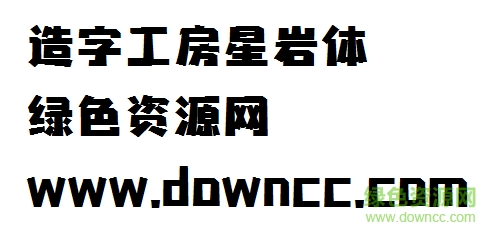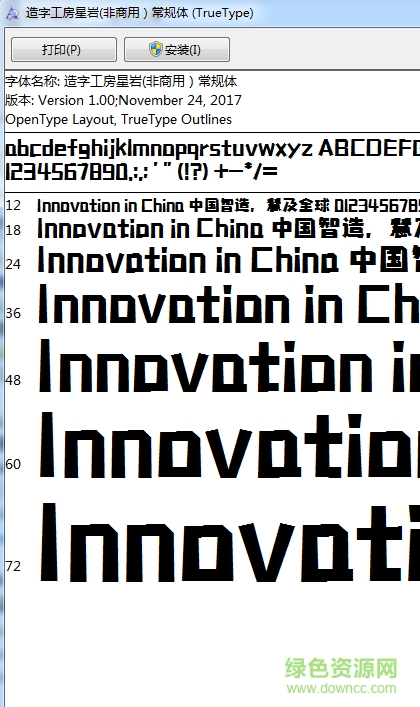
造字工房星巖體粗黑醒目,該字體去除了右上角的棱角,有著獨(dú)特的巖石美感,整體給人非常震撼的效果,喜歡的朋友趕緊下載安裝吧!
造字工房星巖體字體較為完整,能給人十分閱讀清晰的視覺體驗(yàn),無多余的裝飾和點(diǎn)綴,盡顯文字本身的質(zhì)樸和娟秀之美,讓你的藝術(shù)設(shè)計(jì)有用不一樣的書寫體驗(yàn)!